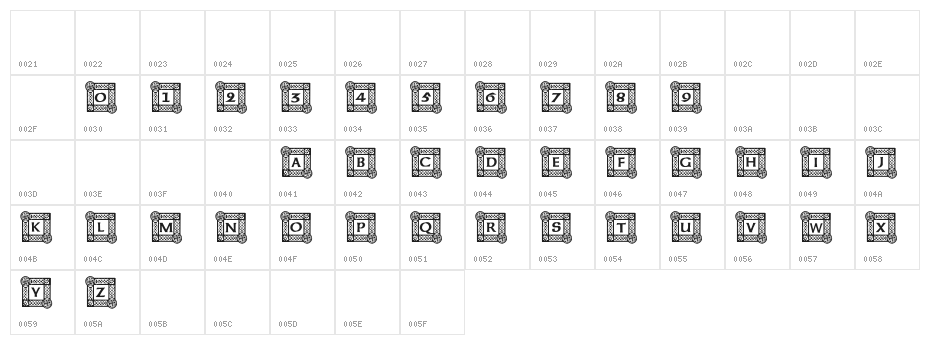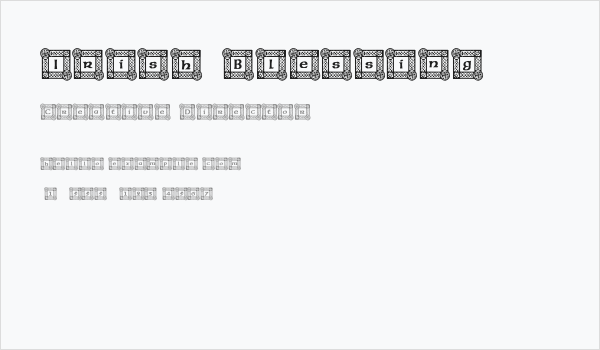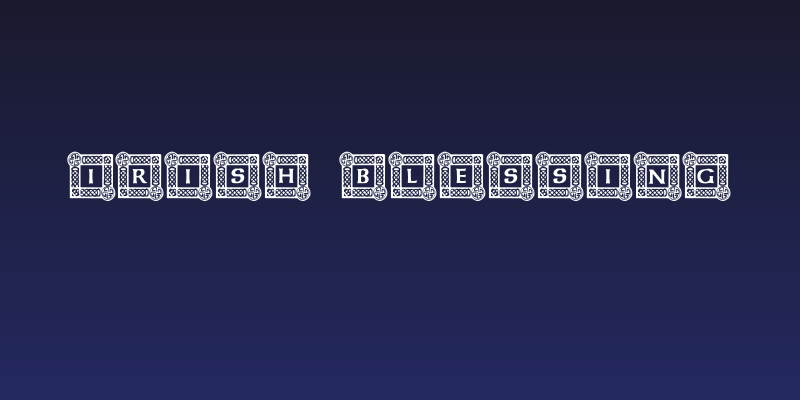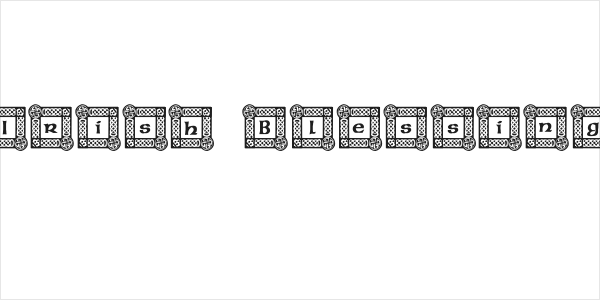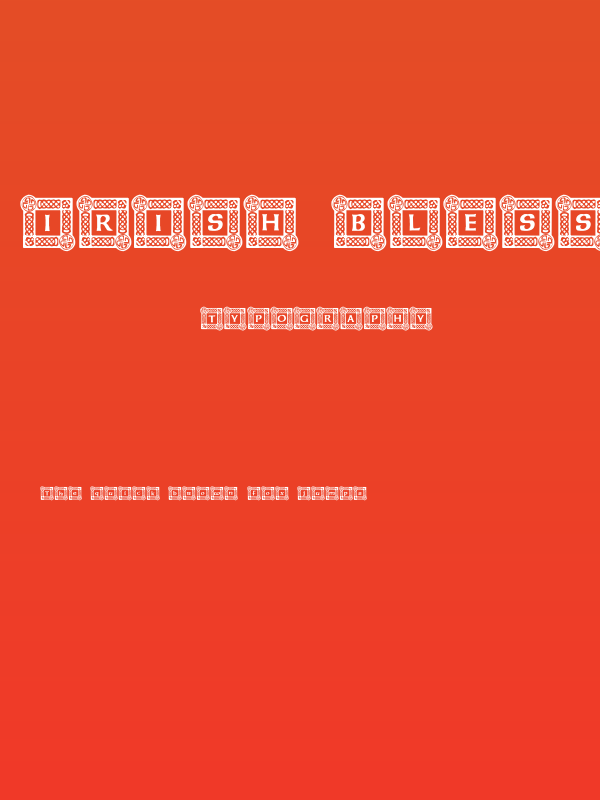
Irish Blessing Font
| Категория | Decorative |
| Область применения | Logos, Headlines, Digital Art |
| Рекомендуемые проекты | Ideal for digital art projects, video game graphics, modern posters, and any design requiring a bold, structured look. |